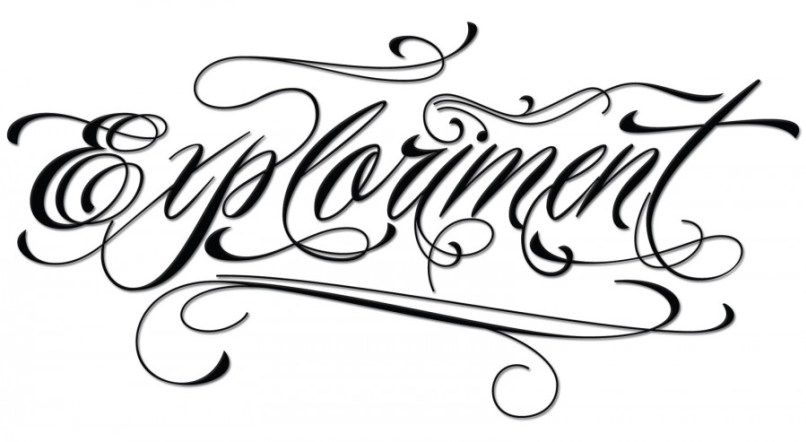
- Как эта татуировка будет формироваться вокруг выбранной мной части тела?
- Мне нужен простой дизайн или что-то, что включает контуры или завитки?
- Что бы я предпочел: цветную татуировку или татуировку в оттенках серого?
Пусть ответы на эти вопросы упростят ваши поиски идеального шрифта для татуировки.
Вложите некоторые исследования и мысли в шрифт вашей татуировки, чтобы создать самое красивое представление о себе.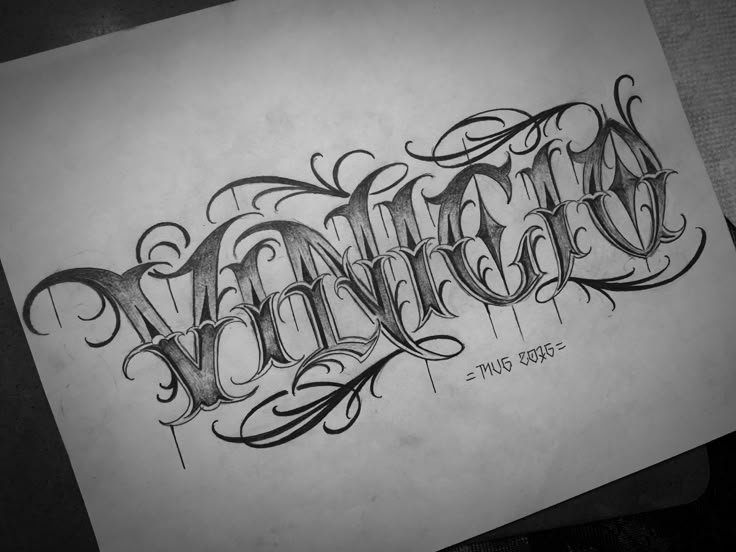